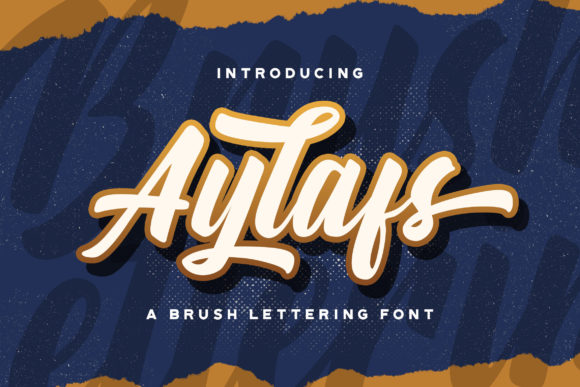
Айлафс - это великолепный и смелый рукописный шрифт, созданный, чтобы придать стильный штрих вашим заголовкам и логотипам проектов.
Этот шрифт читается как сильный, уверенный и динамичный и может придать тонны ностальгического характера вашим дизайнерским работам.